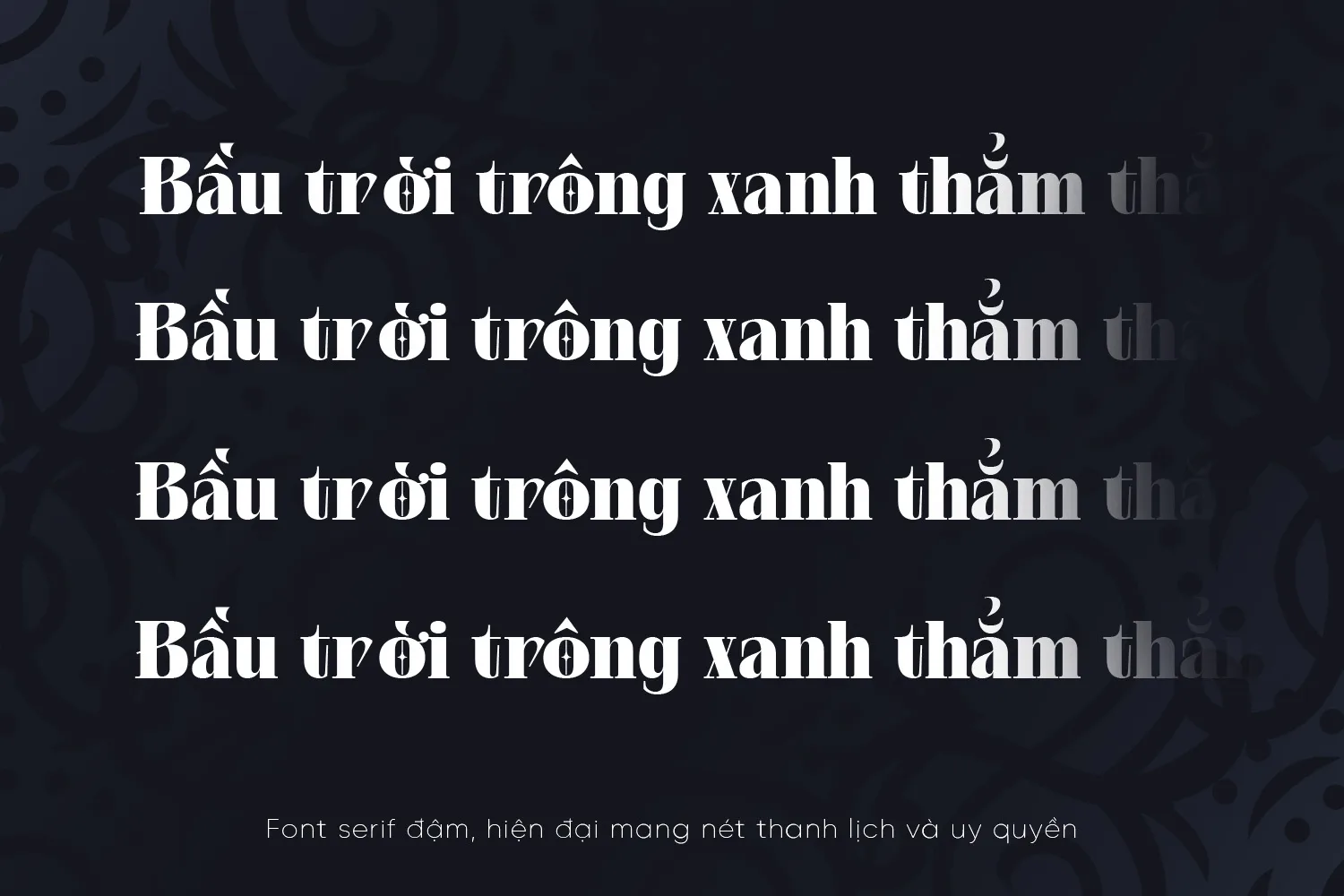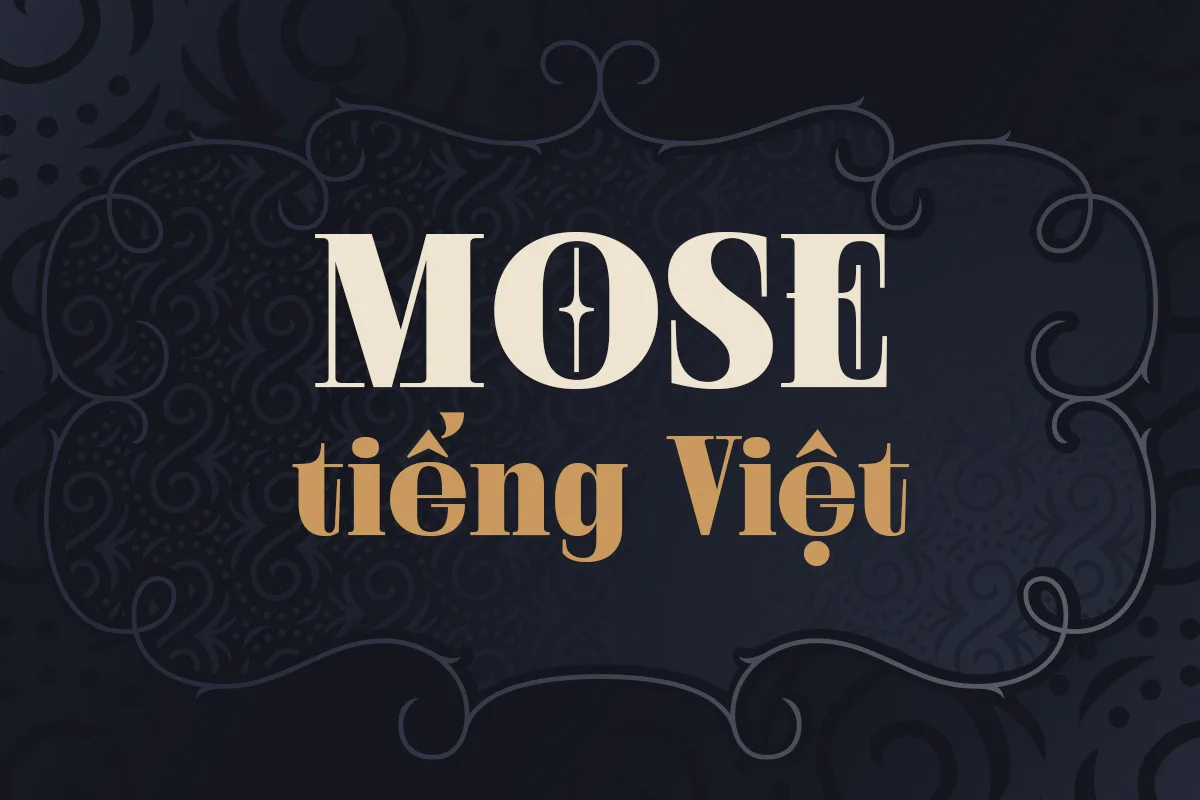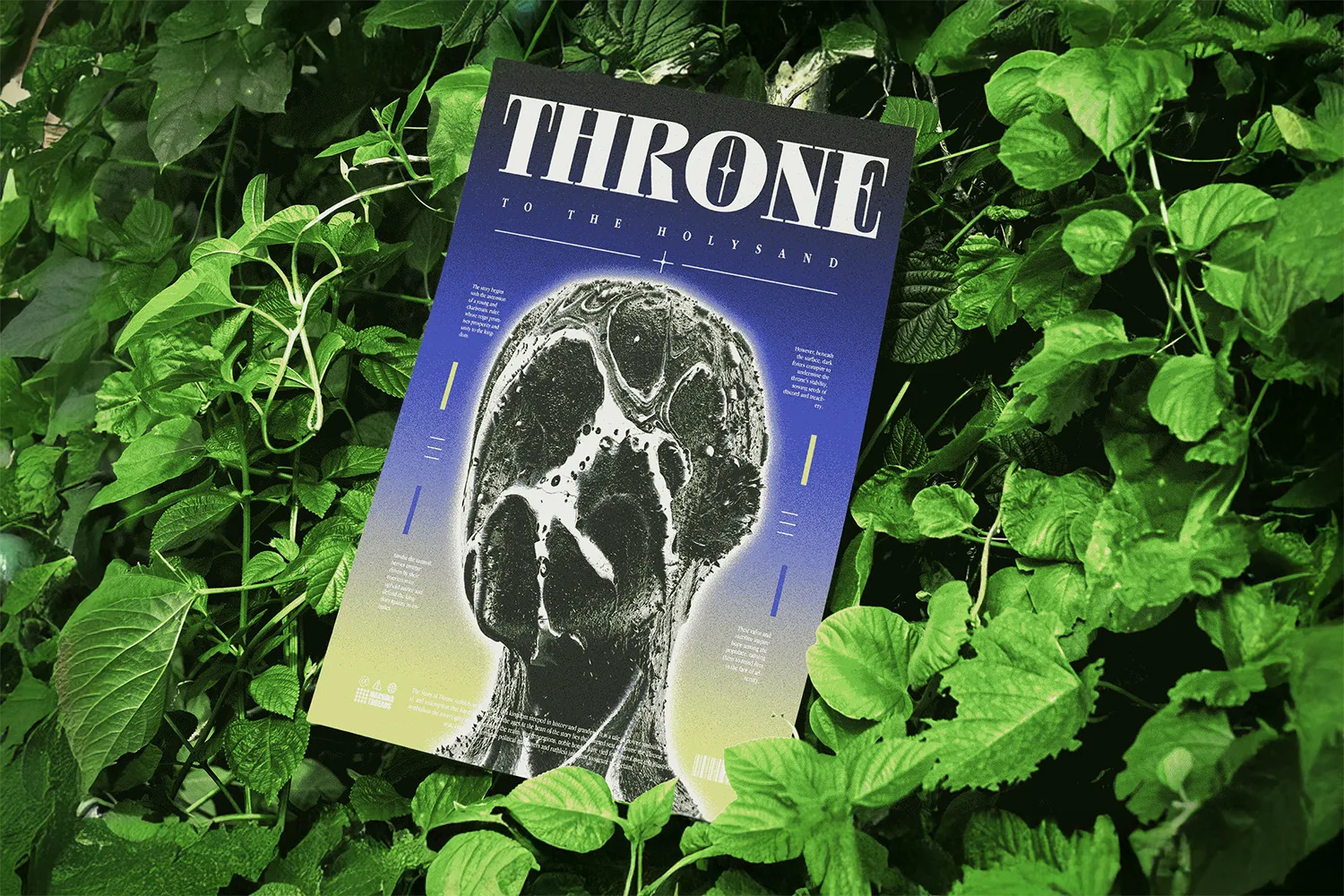
DVN Mose tiếng Việt – Font serif đậm, hiện đại mang nét thanh lịch và uy quyền
DVN Mose là một kiểu chữ serif mang phong cách hiện đại pha chút cổ điển, nổi bật với những đường nét dày – mảnh tinh tế và dấu mũ Việt hóa được thiết kế cân đối. Font thể hiện sự uy nghi, sang trọng và tự tin, rất thích hợp cho thiết kế thương hiệu cao cấp, tạp chí thời trang, bìa sách hoặc tiêu đề quảng cáo.
DVN Mose không chỉ tạo cảm giác mạnh mẽ trong từng ký tự mà còn giữ được vẻ mềm mại, thanh thoát của những đường cong serif truyền thống – giúp nó trở thành lựa chọn hoàn hảo cho các nhà thiết kế yêu thích sự cân bằng giữa cổ điển và hiện đại.